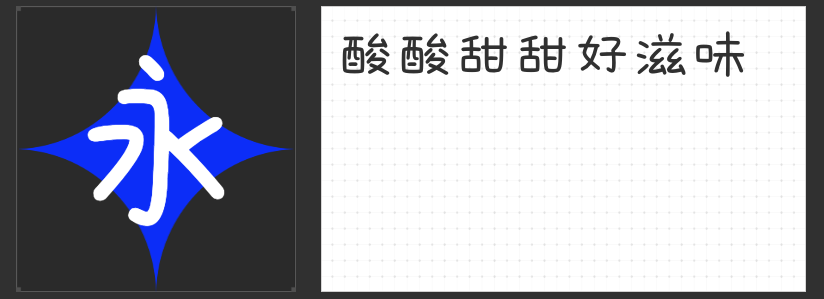
圆润之美:四款特色圆体字体设计应用指南
在视觉设计领域,圆体凭借其温润柔和的视觉特性,成为传递亲和力与现代感的重要载体。本文精选四款兼具艺术性与实用性的圆体字体,解析其设计语言与适用场景,为设计师提供精准选型参考。
一、励字圆梦简 中黑
这款字体以直线笔画构建骨架,通过竖折结构替代传统弧线,形成简洁明快的视觉节奏。其创新之处在于将圆弧元素精准嵌入笔画端点与转折处:起笔处以微弧收尾,收笔时采用半圆过渡,转折点则通过120°圆角处理实现刚柔并济。中宫区域适度留白的设计打破传统圆体的紧凑感,配合外轮廓的椭圆化处理,使字体在保持辨识度的同时,呈现出独特的呼吸感。适用于科技产品界面、年轻化品牌VI系统等需要平衡专业感与亲和力的场景。
二、励字粗圆简繁
作为粗体圆体的典范,该字体通过加粗笔画(字重达700)强化视觉冲击力,却巧妙运用圆角处理消解厚重感。其结构特征可概括为"方正骨架+柔性皮肤":横竖笔画保持等宽设计确保稳定性,折笔处采用150°大圆弧过渡,使字体在端正中透出灵动气质。特别适合用于文化展览海报、传统品牌升级项目,既能彰显庄重底蕴,又通过圆润细节拉近与受众的距离。
三、字圈也字多肉体
这款字体突破常规圆体设计范式,将所有转折点转化为封闭圆环结构,形成独特的视觉符号系统。例如"口"部设计为双圆环嵌套,"辶"旁的捺画末端演变为水滴形圆环。通过"破方为圆"的设计哲学,字体在保持汉字结构完整性的同时,创造出类似卡通形象的趣味性。推荐用于儿童教育产品、文创周边设计,其Q弹可爱的视觉语言能有效激发受众的情感共鸣。
四、字圈也字果酱体
以果酱流动形态为灵感,这款字体构建出矛盾统一的视觉语言:横竖笔画保持75°倾斜角展现动态感,折笔处交替使用90°直角与135°钝角形成节奏变化,局部笔画末端采用滴落状装饰强化主题联想。其"外柔内刚"的设计特质,既适合食品包装、美妆品牌等需要传递甜蜜感的领域,又能通过棱角细节保持现代设计所需的精致感。
这四款字体通过差异化设计策略,拓展了圆体在商业设计中的应用边界。设计师可根据项目调性,灵活运用其结构特征与情感属性,创造出既符合功能需求又具有艺术价值的视觉解决方案。